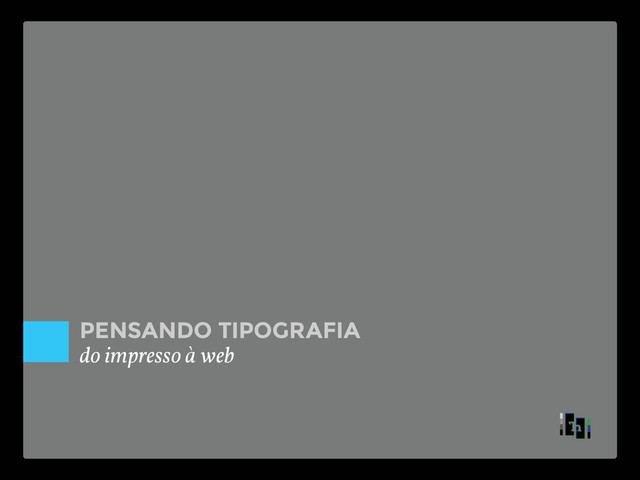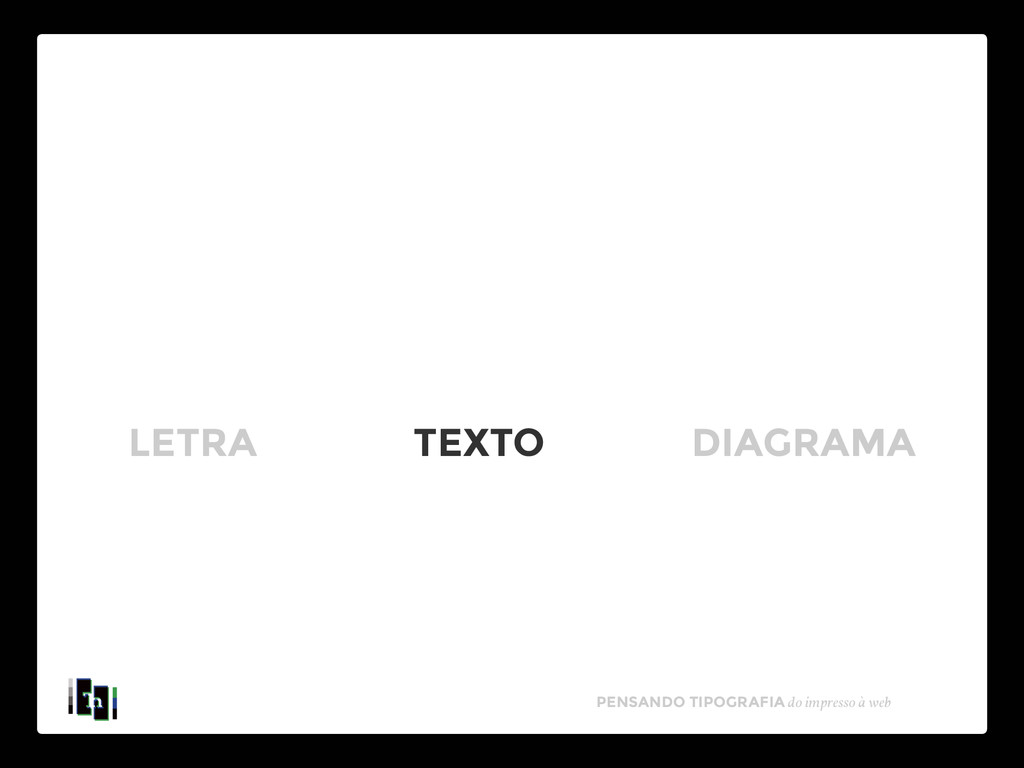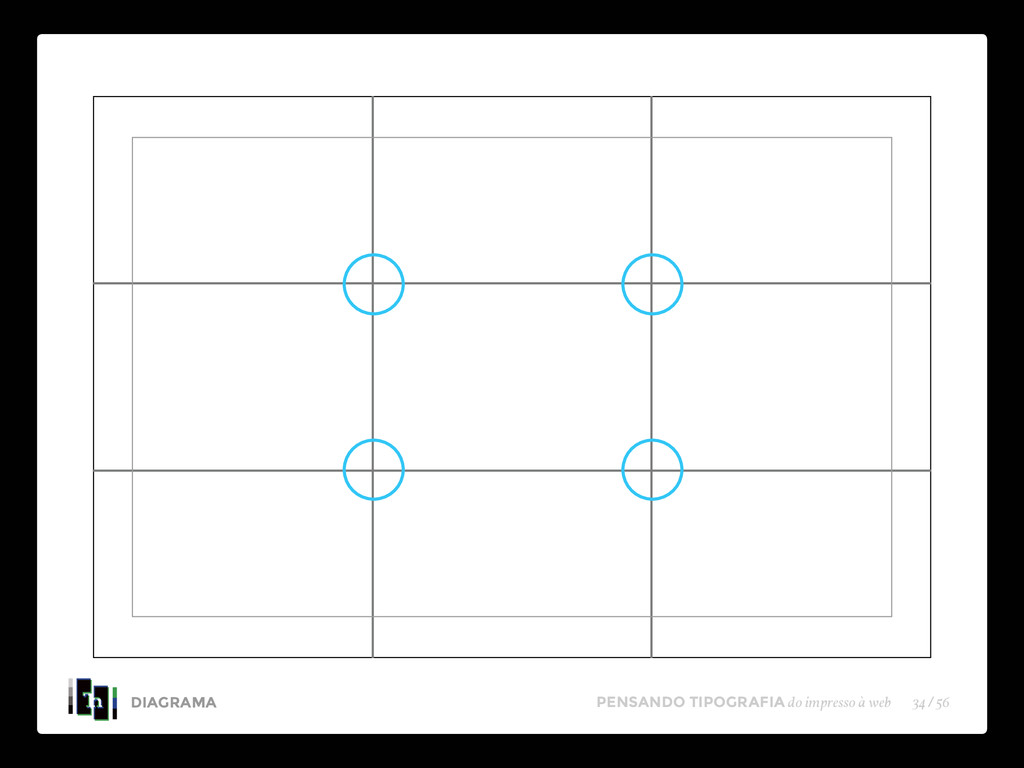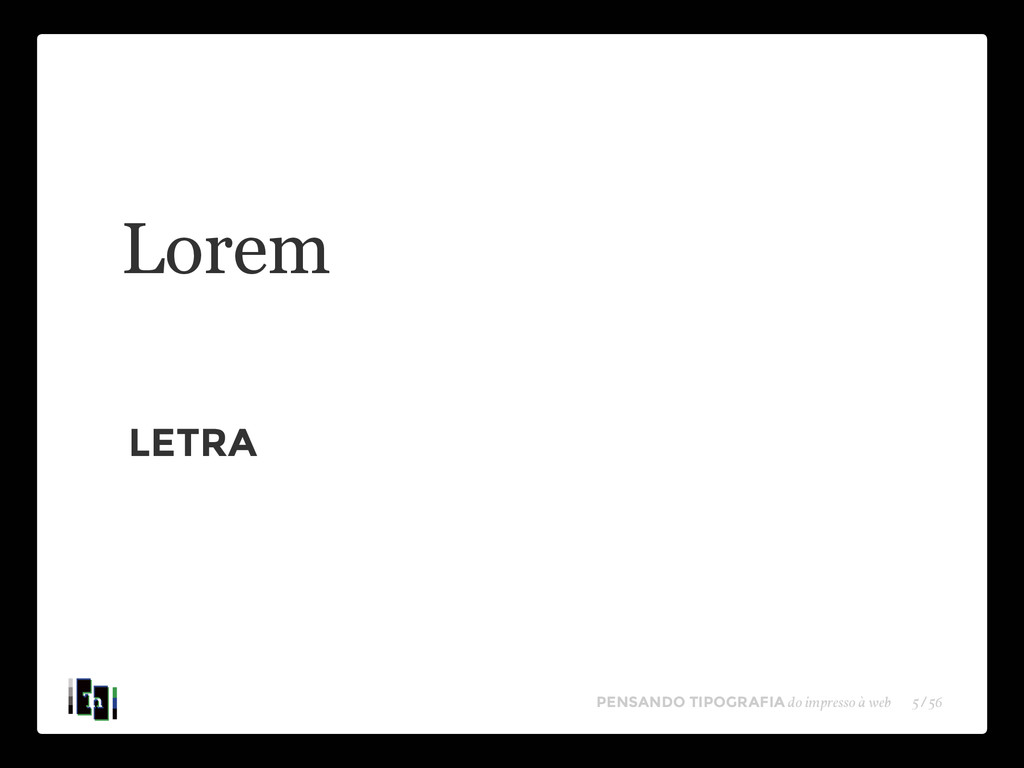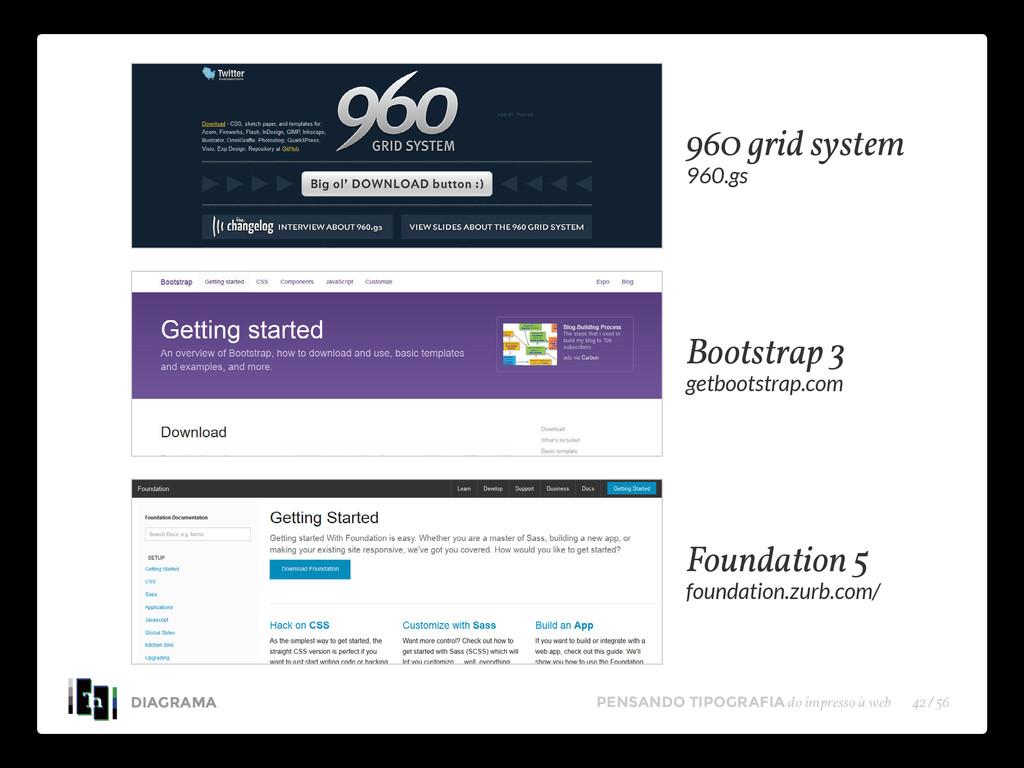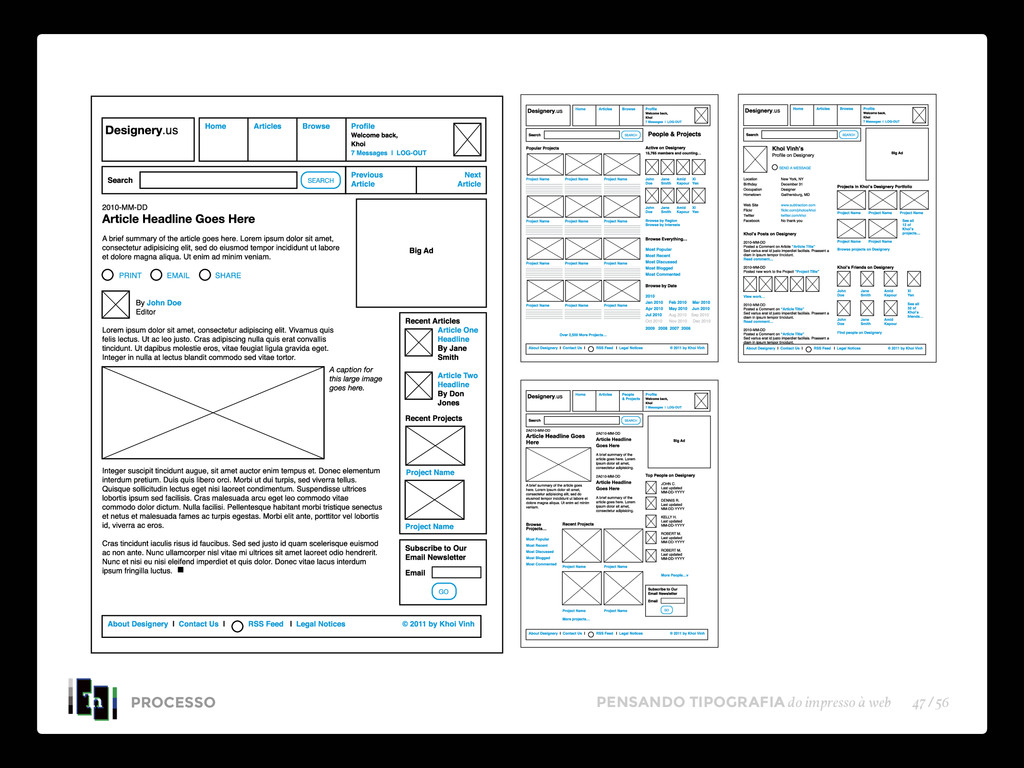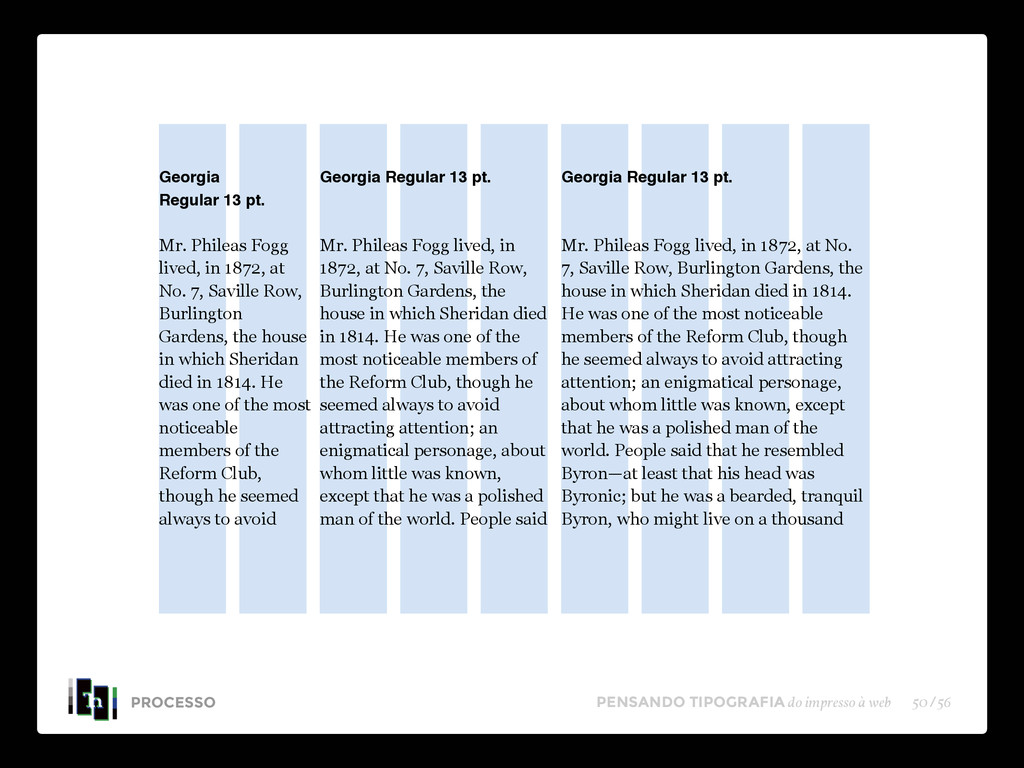
Pensando Tipografia: do impresso à web
Pensando Tipografia: do impresso à web
Aula Magna ministrada na Castelo Branco, apresentando questões práticas da tipografia, desde sua aplicação clássica em impressos até sua revisão e conversão para sites e ambientes digitais